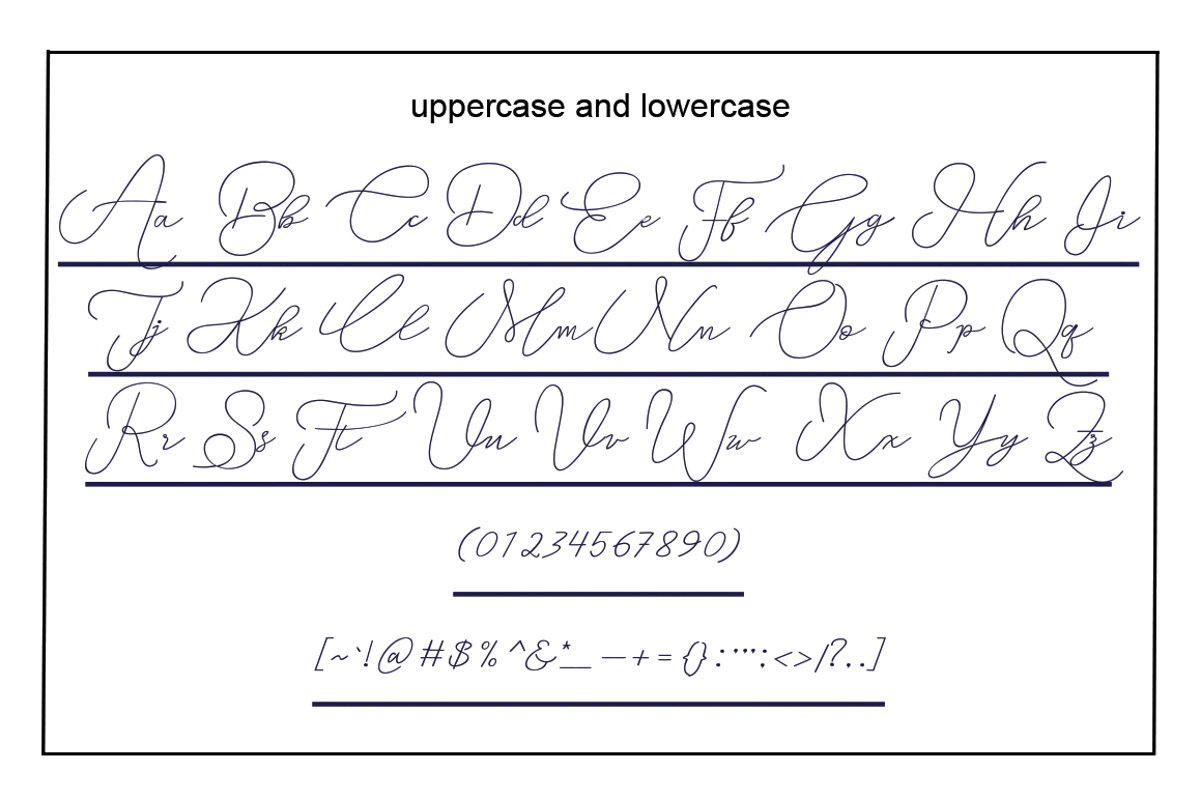
Gta
Hadir: Gta
Font ini dirancang dengan tulisan tangan, dan memiliki bentuk yang halus dan ukuran yang sama, Dapat digunakan untuk berbagai keperluan. Seperti judul, logo, undangan pernikahan, t-shirt, kop surat, papan nama, label, berita, poster, lencana, dll.
Bahasa yang Didukung: Breton, Catalan, Ceko, Denmark, Estonia, Prancis, Jerman, Hungaria, Islandia, Italia, Rumania, Gaelik Skotlandia, Slowakia, Latvia, Lithuania, Norwegia, Inggris, Finlandia, Portugis, Slovenia, Spanyol, Turki, Welsh. Pada dasarnya, semua bahasa Eropa didasarkan pada abjad Latin.